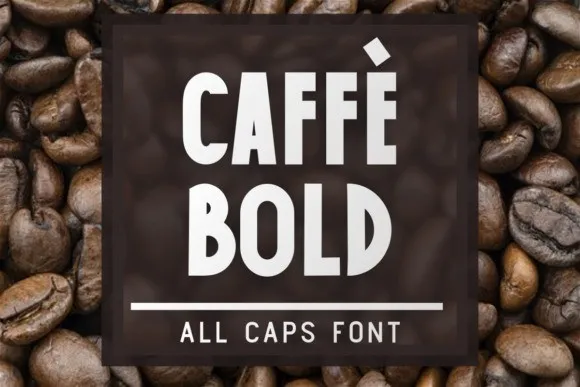
A Caffe Bold Display Font é uma seleção perfeita para aqueles que desejam dar vida a seus projetos digitais com um estilo elegante e contemporâneo. Com sua estrutura clássica, essa fonte sans-serif simples e robusta permite criar alternativas tanto modernas quanto clássicas, tornando-a uma opção versátil para designers gráficos iniciantes e experientes. O designer de 99designs, deedeetype, criou a Caffe Bold Display Font com simplicidade em mente, fazendo dela um recurso que se encaixa perfeitamente em vários tipos de projetos. Seja para criação de materiais de branding, design gráfico, layout editorial ou qualquer projeto visual que você possa imaginar, essa fonte pode ser facilmente adaptada e combina perfeitamente com um amplo conjunto de idéias criativas. Adicionar a Caffe Bold Display Font ao seu próximo projeto é como adicionar um toque definitivo que faz sua obra se destacar. É uma opção de fontes sans-serif ideal para aqueles que desejam incorporar elegância e simplicidade em seus projetos digitais, tornando-os ainda mais memoráveis e profissionais.